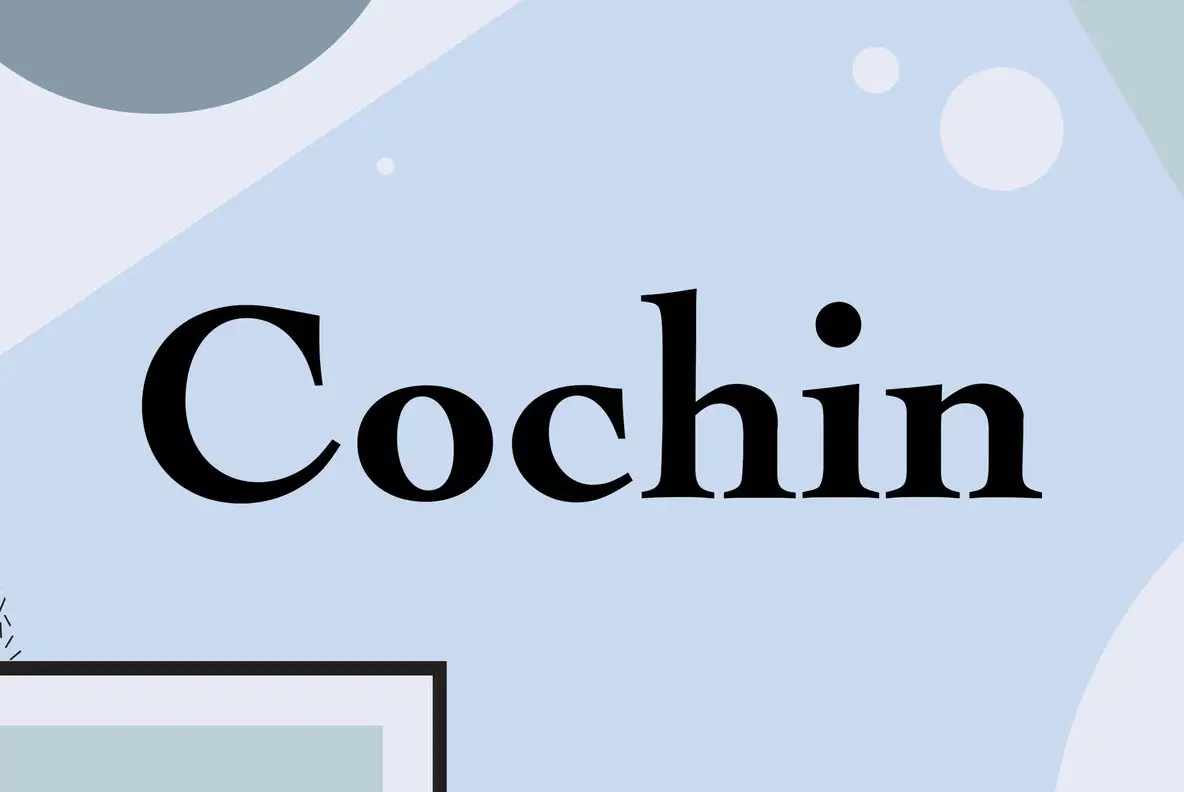
Cochin Font Việt hóa là bộ phông chữ có chân (Serif) mang phong cách cổ điển Pháp vô cùng thanh lịch và nghệ thuật, được sáng tạo bởi Georges Peignot vào năm 1912 cho xưởng đúc chữ Deberny & Peignot. Lấy cảm hứng từ các bản khắc đồng thế kỷ 18 của họa sĩ Nicolas Cochin, phông chữ này sở hữu tỷ lệ chữ độc đáo với chữ hoa thấp và chữ thường vươn cao, mang lại diện mạo hoài cổ, trí tuệ và vô cùng sang trọng. Doozypack.vn cung cấp link Cochin Font Free download chuẩn kỹ thuật, giúp bạn sở hữu phông chữ đẳng cấp này, hỗ trợ đầy đủ tiếng Việt để tự tin thiết kế bao bì và bộ nhận diện thương hiệu chuyên nghiệp.
Đặc điểm thẩm mỹ độc đáo của bộ font Cochin
Cochin không đi theo các tỷ lệ tiêu chuẩn của trường phái La Mã; nó mang đến một ngôn ngữ thị giác đầy tính điện ảnh, gợi nhắc đến những trang sách cổ của Paris và các thương hiệu nước hoa xa xỉ.
Phong cách French Transitional Serif mang hơi thở nghệ thuật thế kỷ 18
Đặc trưng lớn nhất của Cochin Font Việt hóa là sự pha trộn giữa nét cổ điển và tính linh hoạt hiện đại. Các đường nét gạch chân (serif) của Cochin có phần chân hơi loe nhẹ và không quá sắc nhọn, tạo cảm giác mềm mại, ấm áp nhưng vẫn vô cùng trang trọng. Khi đặt Cochin làm tiêu đề trên bao bì, sản phẩm của bạn sẽ ngay lập tức toát lên vẻ ngoài tinh tế, trí thức và mang đậm chất thơ của kinh đô ánh sáng.
Tỷ lệ chữ độc đáo với chữ hoa thấp và chữ thường vươn cao
Một điểm nhận diện thú vị của Cochin Bold Font và các biến thể thông thường là chiều cao của các chữ cái thường (ascenders) vươn khá cao so với chữ cái in hoa. Tỷ lệ hình học này tạo ra một nhịp điệu Typography rất riêng biệt, giúp các đoạn văn bản mô tả hoặc tiêu đề phụ trông thoáng đãng, uyển chuyển và không hề bị nặng nề.
Ưu điểm nổi bật của bản Cochin Font Việt hóa
Khi ứng dụng các phông chữ mang âm hưởng nghệ thuật Pháp vào thị trường trong nước, sự chỉn chu về dấu câu là yếu tố quyết định đến tính chuyên nghiệp của ấn phẩm:
- Khắc phục triệt để lỗi dấu tiếng Việt: Phiên bản Việt hóa đã được đội ngũ thiết kế trau chuốt thủ công từng dấu câu. Các dấu sắc, huyền, hỏi, ngã, nặng được vẽ với tỷ lệ cân đối, đặt ở vị trí thoáng đãng so với thân chữ, không gây cảm giác chắp vá hay đè nét làm mất tính thẩm mỹ Pháp cổ.